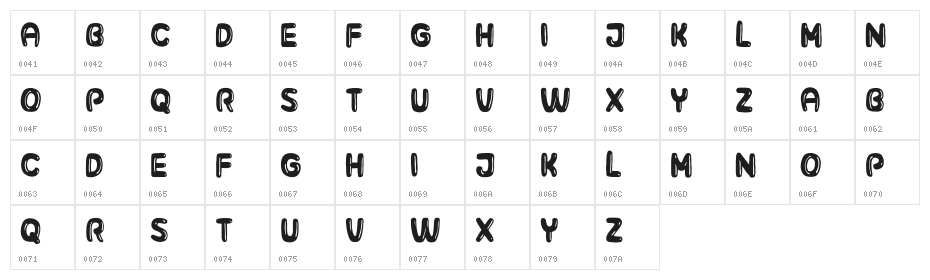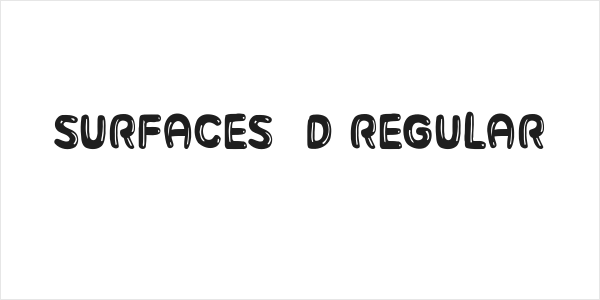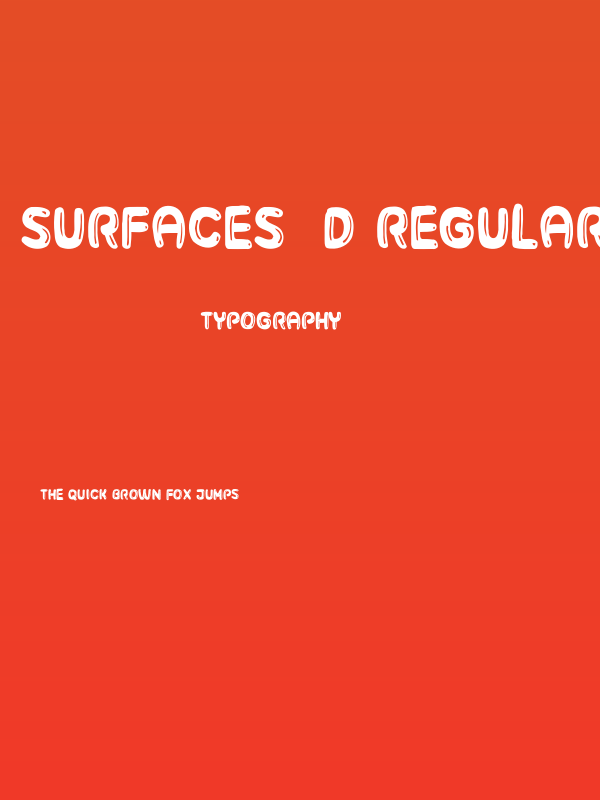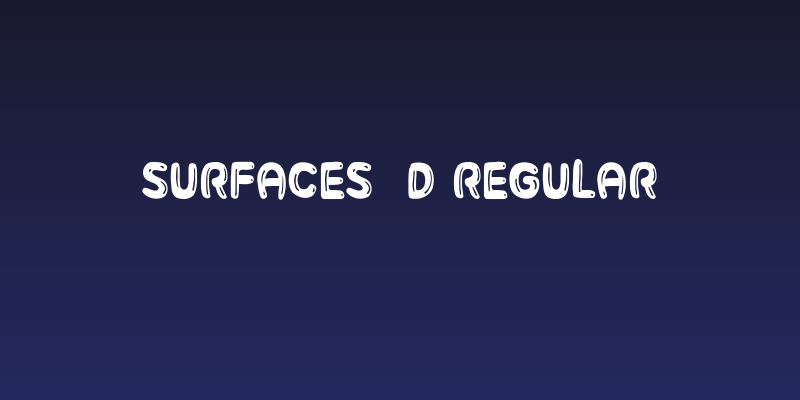
Surfaces 3D Regular Font
| चौड़ाई | Condensed |
| समग्र शैली | Playful, Cartoon-like, Decorative |
| उपयोग का मामला | Headlines, Logos, Posters |
| सुझाए गए प्रोजेक्ट | Ideal for children's book covers, playful posters, video game graphics, and any project needing a fun, dynamic look. |